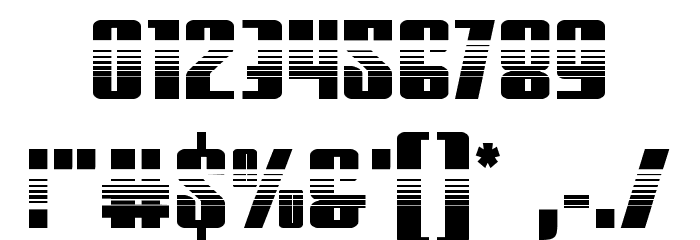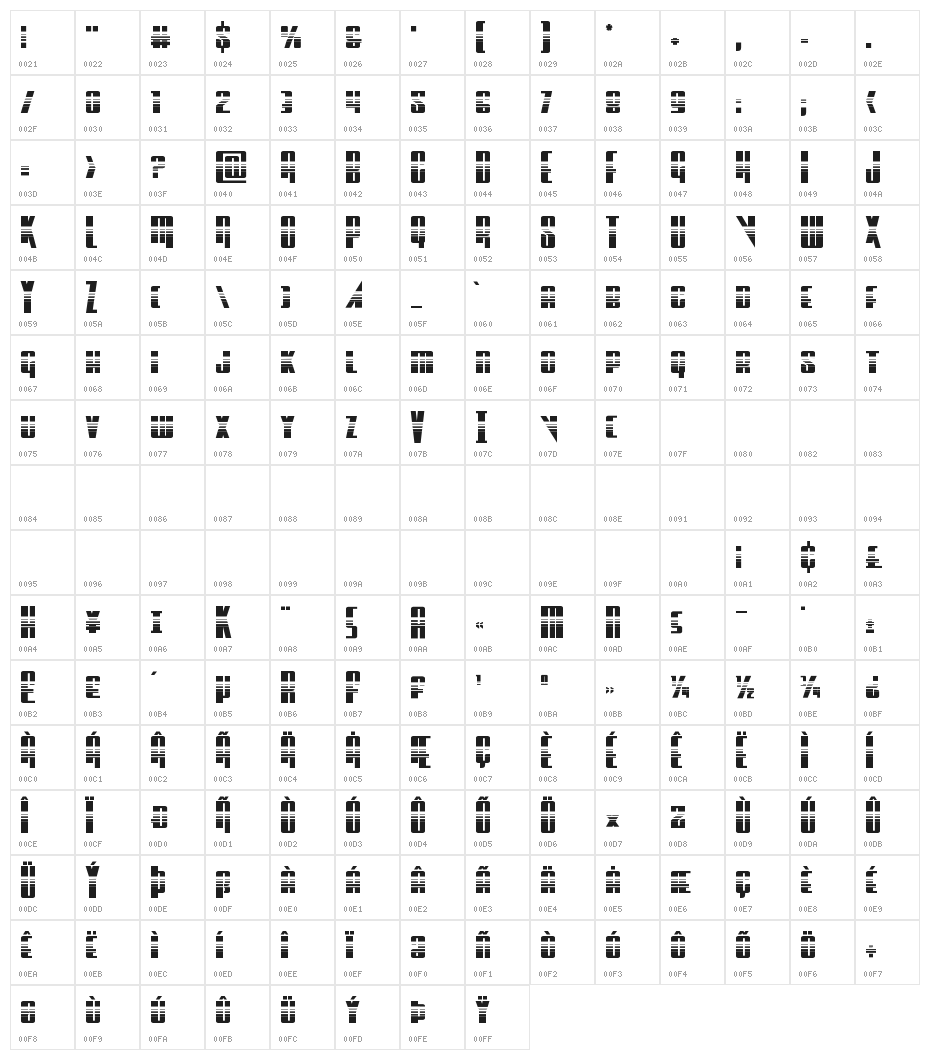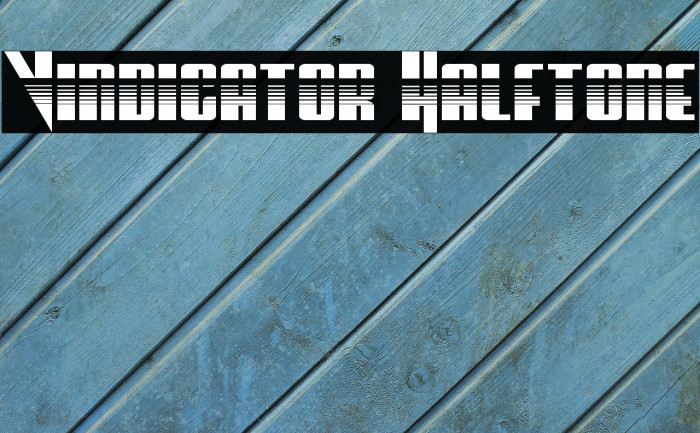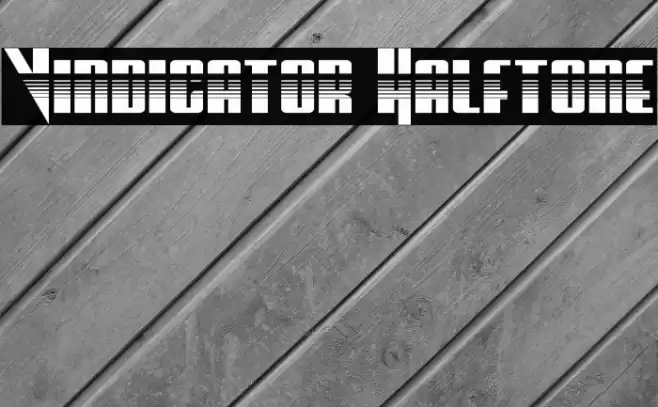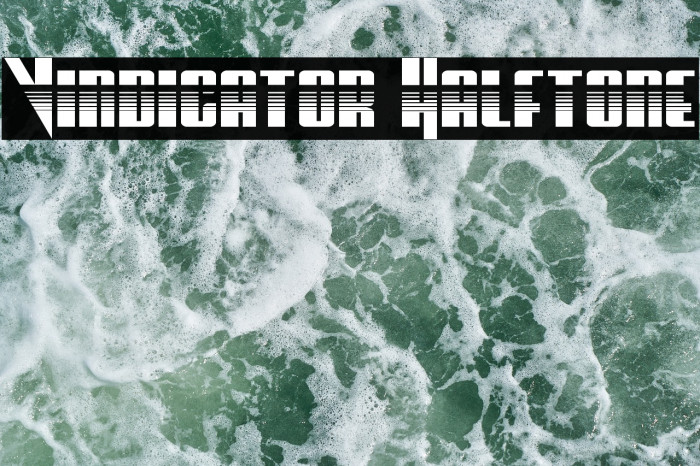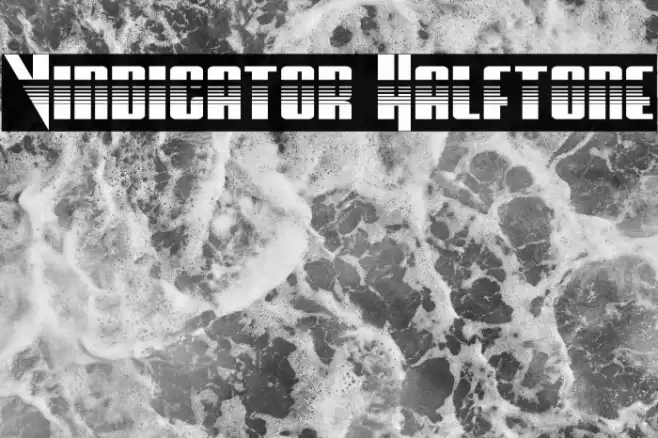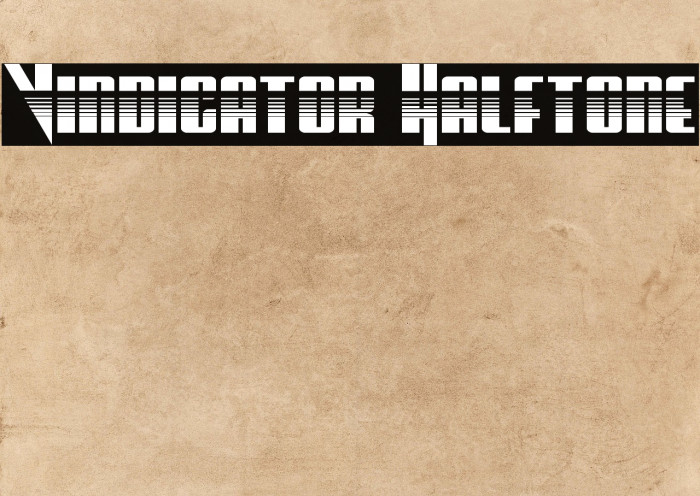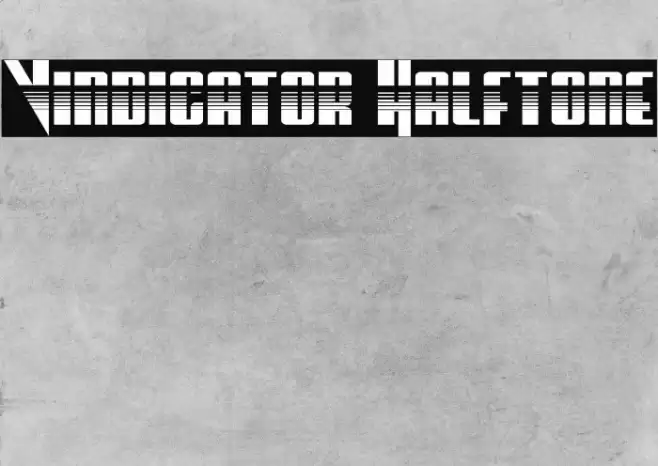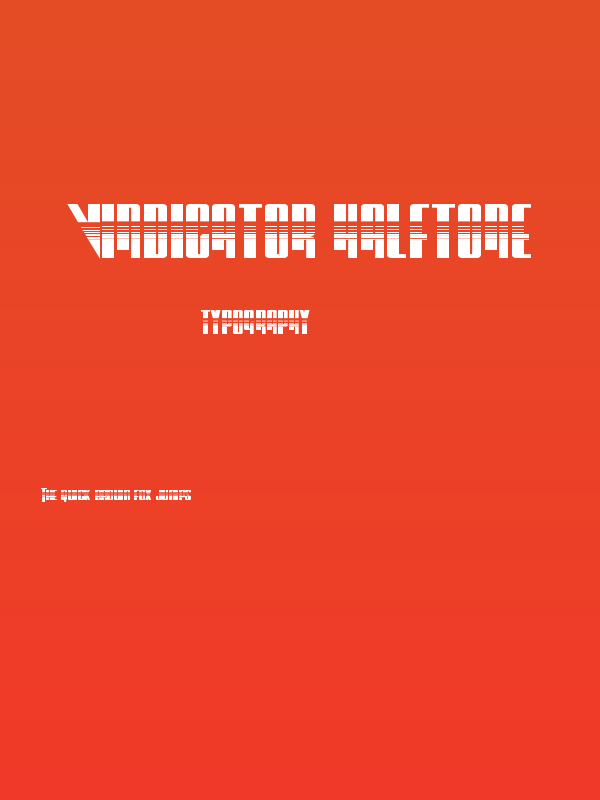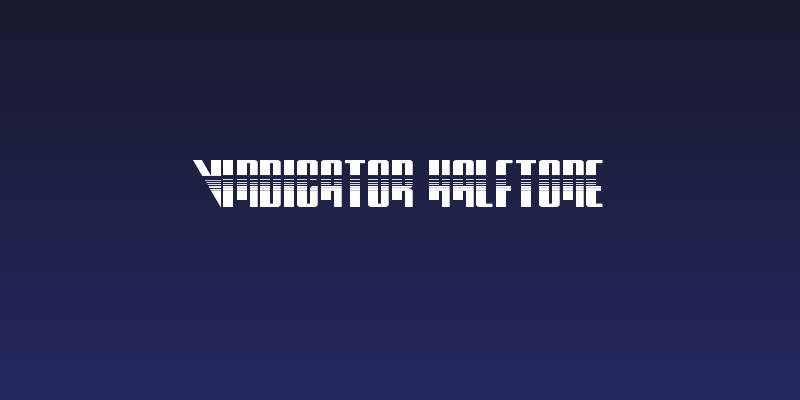
Vindicator Halftone Font
| उपयोग का मामला | Headlines, Logos, Posters |
| सुझाए गए प्रोजेक्ट | Ideal for posters, album covers, branding, and any project needing a bold, modern aesthetic. |